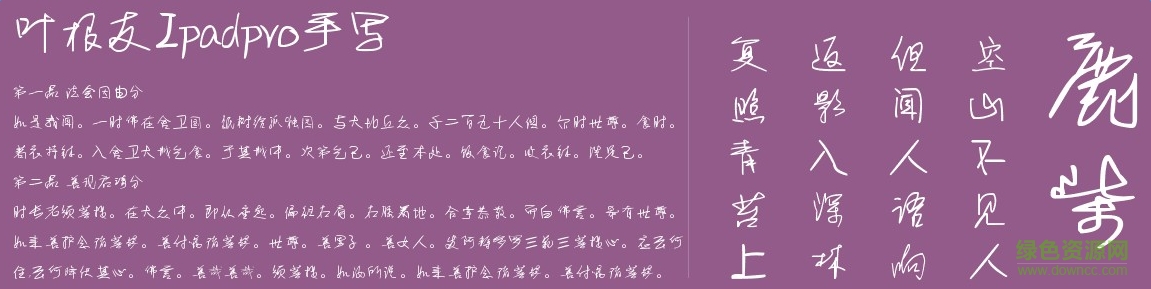
葉根友ipad pro手寫字體是一款由知名書法家葉根友創(chuàng)造的字體,適用于廣告設(shè)計(jì)、藝術(shù)、海報(bào)設(shè)計(jì)等方面,有需要的朋友們不要錯過了。小編為大家提供免費(fèi)下載地址。歡迎大家來綠色資源網(wǎng)踴躍下載哦!
一位從事設(shè)計(jì)創(chuàng)意的好友唐曾平先生的一句話建議,說是否可以用ipad pro來寫字體...
于是開始了這款字體的創(chuàng)作,
這是利用ipad pro寫字版用手指寫的字體
充分用碎片時(shí)間來書寫,候車廳、床上、辦公室都留下了她的身影
讓書法與現(xiàn)代高科技的結(jié)合,指隨心動方式來創(chuàng)作字體的感覺很好
一種新型工具的一種嘗試,雖然不太好寫,經(jīng)過幾個(gè)月的努力,總算是把6763個(gè)漢字寫好了
葉根友ipad pro手寫字體,用途廣泛,是葉根友先生的手寫字體,字體非常靈巧生動,適用于藝術(shù)設(shè)計(jì)等方面。各位字體收藏者可以來看看。